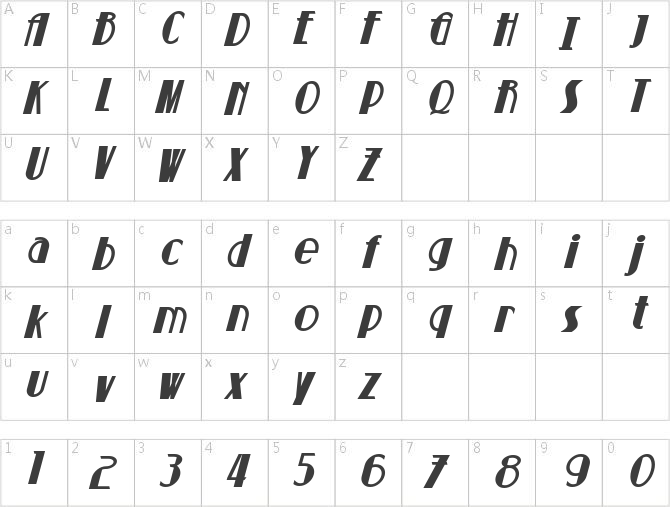
Suchet Bold Italic
Suchet Bold Italic介紹
Suchet Bold Italic字體字庫是一款讓人賞心悅目、百看不厭的英文字體,適合各類廣告和產(chǎn)品包裝設(shè)計應(yīng)用,字體大小0.03MB,格式為ttf字體,上傳用戶是雅迪,作者/版權(quán)方為未知